さける昆布
「さける昆布」は、北海道産100%の昆布を気持ち良くさいて食べることができるお菓子で、昆布をそのまま使用しているので、そのうま味が活かされた自然な味になっており、食物繊維とカルシウムがたっぷり含まれているのも特徴。
食材評価制度「ジャパンフードセレクション」の2015年金賞を受賞している。
さける昆布のタイトルにダイナフォント龍門石碑体が採用
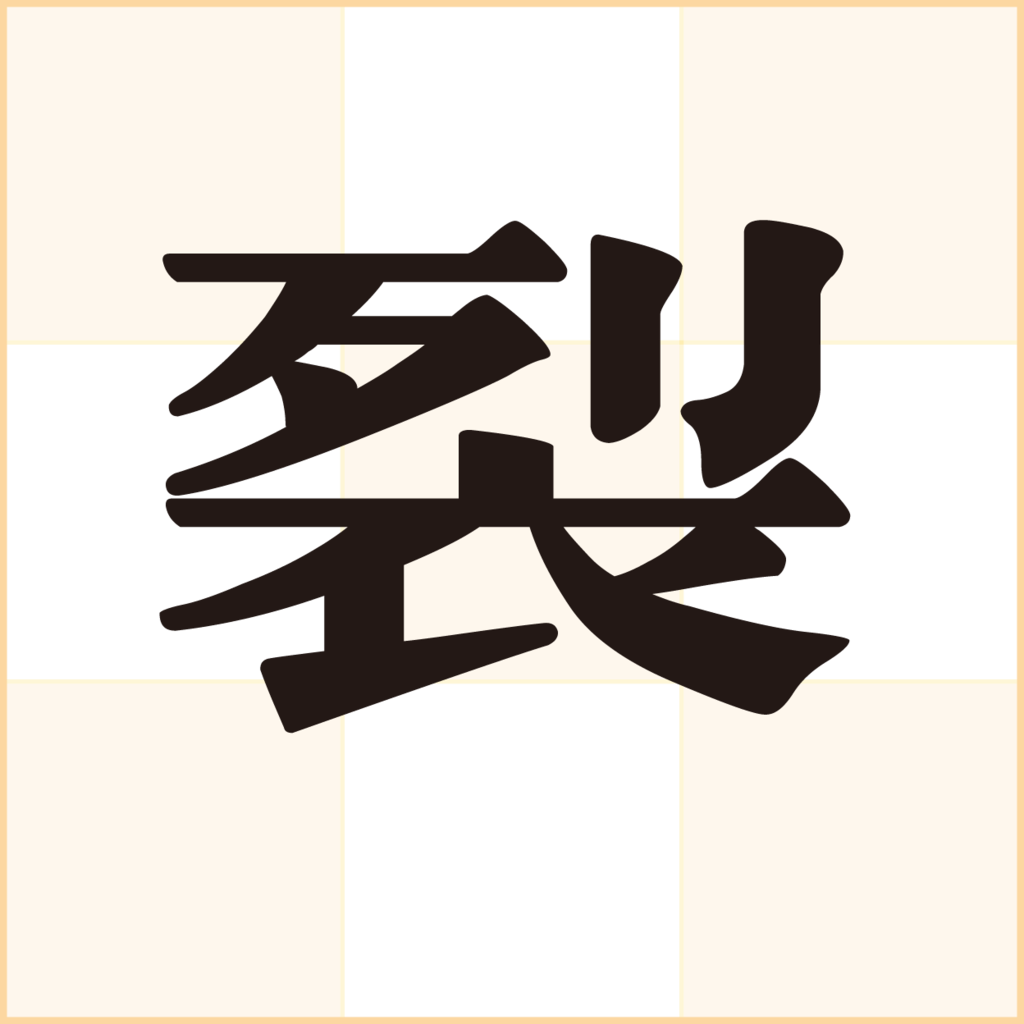
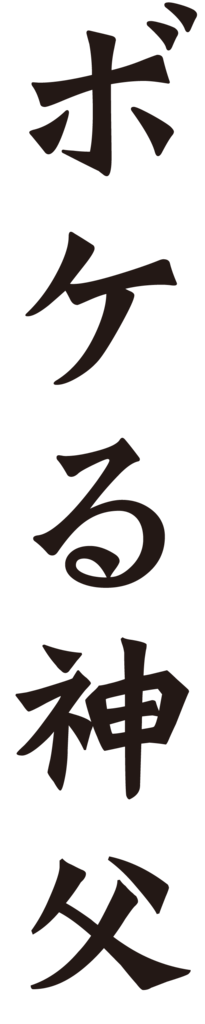
株式会社くらこんホールディングスが製造・販売している「さける昆布」に「ダイナフォント 龍門石碑体」が採用されている。
龍門石碑体
「龍門石碑体」は中国の龍門石窟に刻まれた力強さと独特の風格を備えた北魏の名品と言われる書体様式と特長を持った書体。無造型に彫ったような字形と線質は、細かいことに拘泥しない強い雰囲気をたたえており、その奥に充分に計算された全体のバランスが感じられる。
落ち着いていて重々しい中にも鋭角的なきっぱりとした味わいがあり、アレンジ楷書を使用したい時などにオススメ。